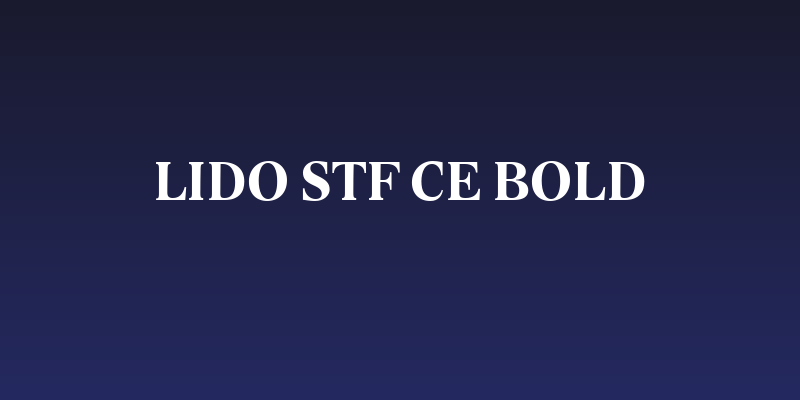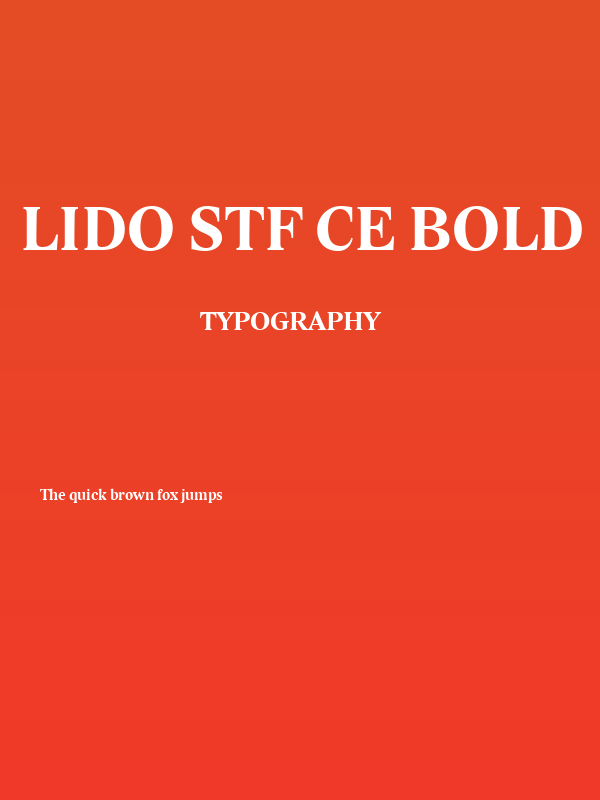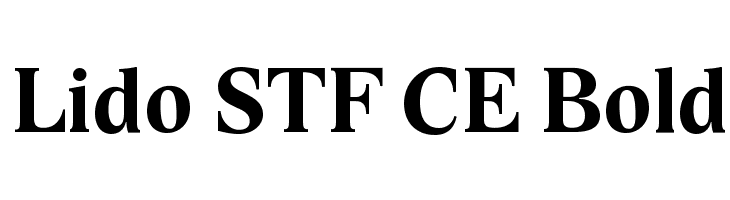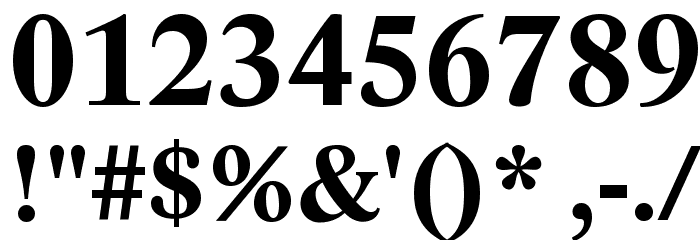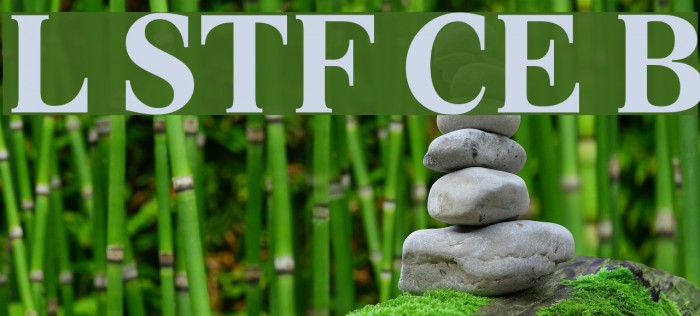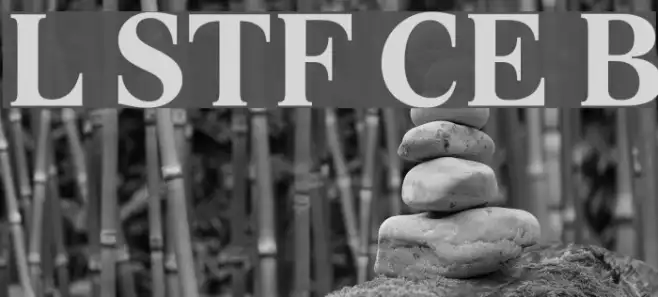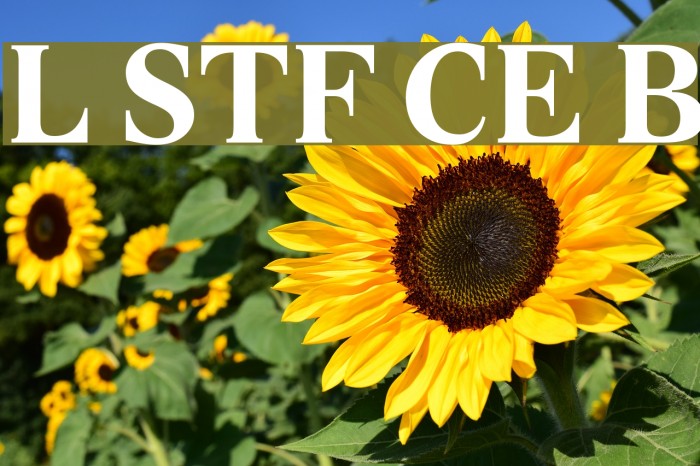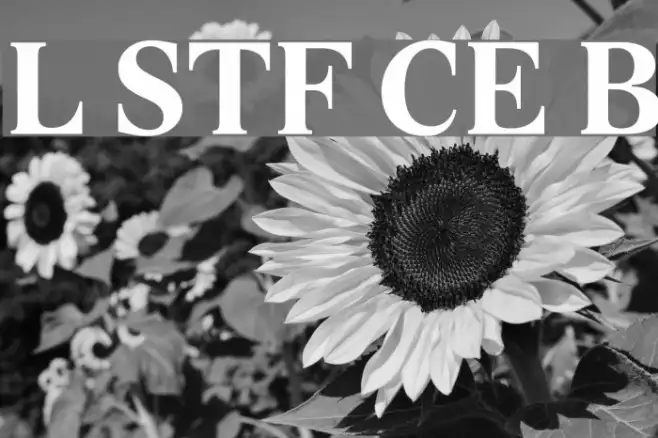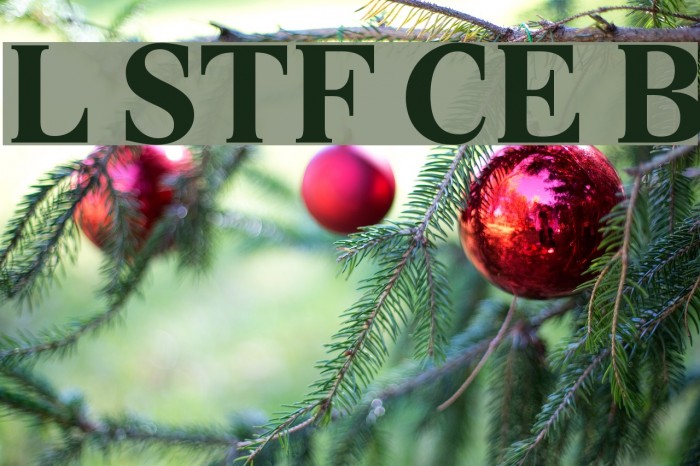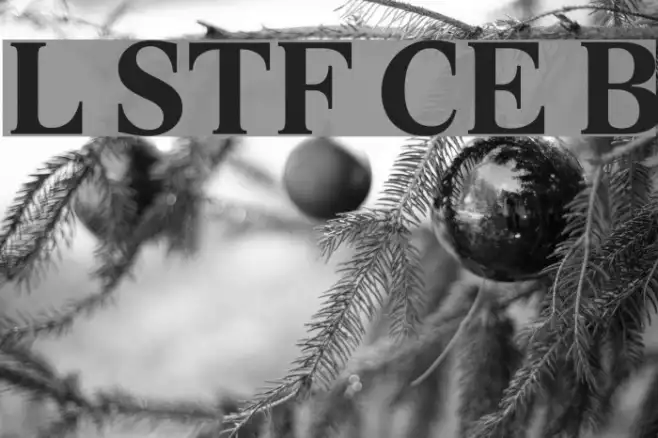
Lido STF CE Bold Font
✎ Serif
| Catégories | Serif |
| Style général | Classic |
| Projets proposés | Ideal for book covers, formal invitations, corporate branding, and editorial headlines. |
Lido STF CE Bold